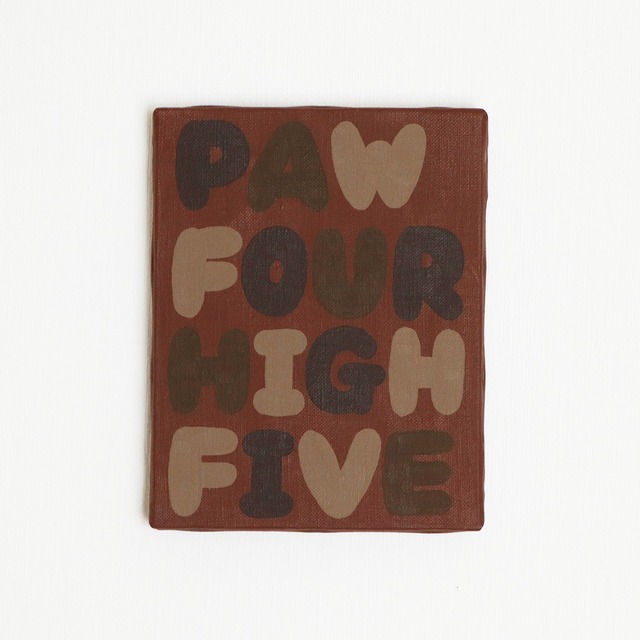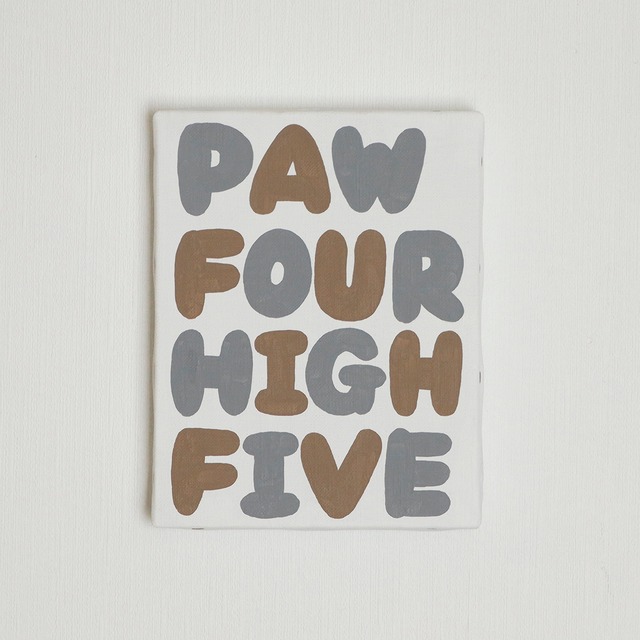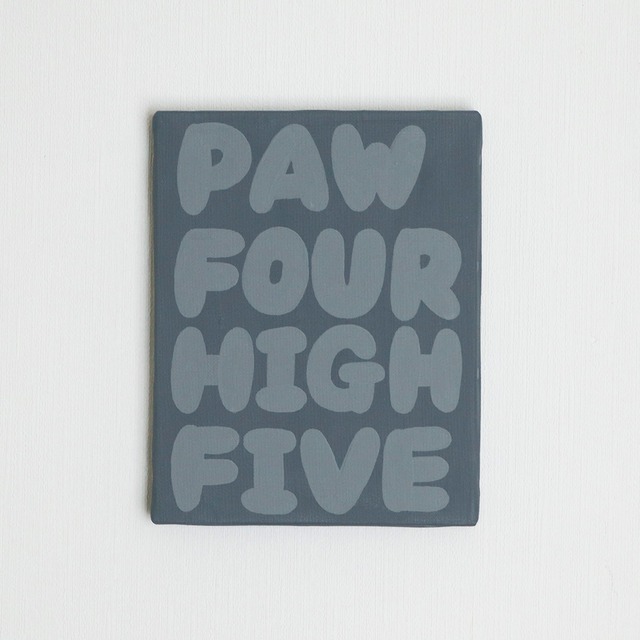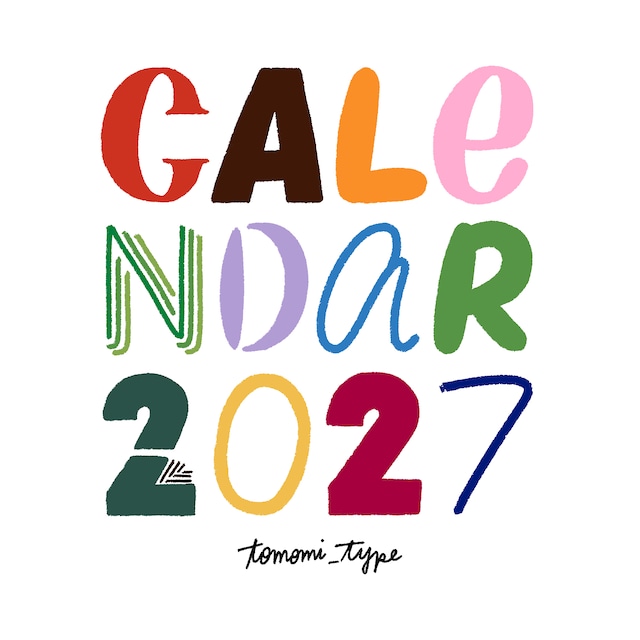
FONT CALENDAR 2027(卓上)
毎年恒例の卓上カレンダーが完成しました! 2027年もワクワクするようなカレンダーに仕上がっています◎ 【1月】Every moment is a fresh beginning / 一瞬一瞬が新たな始まり 【2月】I would rather take chocolate than compliments just now / 今は褒め言葉よりチョコがほしい 【3月】spring fever / (春先のワクワクした高揚感のこと) 【4月】Good luck with your APRIL start! / 4月の新しいスタートに幸運を! 【5月】Smell that fresh MAY air / 新鮮な5月の空気を感じましょう 【6月】Right as rain / 順調そのもの 【7月】catch some waves / チャンスを掴む 【8月】Life is full of ups and downs / 人生は山あり谷あり 【9月】Open book / (多様な考えに寛大であること) 【10月】The fruit of your own hard work is the sweetest / 努力は身を結ぶ 【11月】Good talking to you & Have a good day! / 話ができて良かったです & 良い1日を! 【12月】Everything will turn out for the best / すべては最高の結果になる ----------------------- 【サイズ】 納品時:10.5cm×20.5cm 組立後:10.5cm×16.5cm(h)×9cm
words flower CALENDAR 2027(壁掛け/A4サイズ)
words flowerシリーズは、文字だけで描いたお花です。 今回なんとカレンダーにしました! その月の誕生花を描いています。 A4サイズの壁掛けタイプです。 画鋲やフックなどを使って飾れます(針は少し長めものだと安定すると思います) ポスターのように楽しんでいただけたら嬉しいです◎ 【1月】スイートピー 【2月】アネモネ 【3月】チューリップ 【4月】アルストロメリア 【5月】カーネーション 【6月】アジサイ 【7月】トルコキキョウ 【8月】ヒマワリ 【9月】ダリア 【10月】ガーベラ 【11月】ユリ 【12月】バラ ※誕生花には諸説あります。 ------------------ 【サイズ】 A4サイズ
HANDWRITTEN FONT DICTIONARY LESSON BOOK/ 文字ばかり描いてるイラストレーターのオリジナルフォント描き方練習帖
\オリジナルフォント描き方練習帖ができました!/ オリジナルフォント字典のLESSON BOOKが完成! 「HANDWRITTEN FONT DICTIONARY」を発売してから、 「マネしたいけど上手く描けません…」というお声をいただくことが増えました。 であれば、トモミタイプのオリジナルフォント専用LESSON BOOKを作ろう! となりまして、ついに2冊目となる本が完成しました〜!!! 上手く描けるようになるコツ、フォントのアレンジ法、少しですが新しいフォントも載っています。 この本だけでも楽しめますが、HANDWRITTEN FONT DICTIONARYがお手元にあると より文字を描くのが楽しくなると思います◯ ぜひこれを見ながらたくさん手描きしてみてくださいね^^ ※アレンジ、描き方のページのSNS投稿などはご遠慮ください。 【サイズ】14×14×1(cm) 【ISBNコード】ISBN 978-4-907151-55-3 C0071 ¥1800E 【ページ数】66ページ
HANDWRITTEN FONT DICTIONARY 文字ばかり描いてるイラストレーターのオリジナルフォント字典
\トモミタイプオリジナルフォント字典ができました!/ 文字ばかり描いてるイラストレーター、トモミタイプのオリジナルフォント字典。 既存のフォントを参考にせず、自分で思いついたフォントを絵のように描く私、トモミタイプ。 普段使いしやすいフォントから、思わず描いてみたくなるフォントや季節限定のフォントなど、133種類を一冊にまとめました。 アルファベット大文字・小文字・数字が掲載されています。(一部除く) 眺めるもよし、見様見真似で描いてみるもよし。使い方はあなた次第です! 【サイズ】14×14×1(cm) 【ISBNコード】ISBN978-4-907151-44-7 C0071 ¥1800E
Habit is a second nature
Habit is a second nature 習慣は第二の天性なり 自分の話になりますが、毎朝日付と曜日を描いてSNSにアップする、という習慣があります。 気づけばもう11年半以上(?!)続けている朝の習慣です(2026年9月現在) 正直辞めどきが分からない感がありますが… それでも「続けている」ということが武器になっているのは事実。 そんな自分の気持ちをちょっとだけ込めた作品になっています。 ○サイズ:約227×158×20mm ◯重さ:約150g ○水性塗料使用 ○壁掛け用紐付(仮結びのため使用する場合はしっかりと結び直してください) ◯送料込み 【金額・送料について】 ¥10,000以上の商品のため送料が無料扱いとなっておりますが、大切な作品なので梱包をしっかりした状態でお届けしたいと考えております。 BASEでは、展示会やPOP UPなどで記載している金額に送料を追加した金額となっております。 対面で販売している時と金額が異なりますので、あらかじめご了承くださいませ。
He that falls today may rise tomorrow
He that falls today may rise tomorrow 直訳だと「今日倒れた人は明日は立ち上がるかもしれない」 日本語のことわざに当てはめるなら「七転び八起き」 フレーズ自体には「8」は入っていませんが、 七転び八起きから取って数字の「8」をモチーフにしています。 今日よりも明日、転んだら起き上がりたい。 へこたれそうな時にオススメの作品です。 ○サイズ:約270×220×20mm ◯重さ:約180g ○水性塗料使用 ○壁掛け用紐付(仮結びのため使用する場合はしっかりと結び直してください) ◯送料込み 【金額・送料について】 ¥10,000以上の商品のため送料が無料扱いとなっておりますが、大切な作品なので梱包をしっかりした状態でお届けしたいと考えております。 BASEでは、展示会やPOP UPなどで記載している金額に送料を追加した金額となっております。 対面で販売している時と金額が異なりますので、あらかじめご了承くださいませ。
NO BOOK NO LIFE
NO BOOK NO LIFE 本なしでは生きられない! よく見ると全部「本」のフォントになっています。 こういう方、たくさんいらっしゃるのでは?と思いながら描きました。 本好きの方へのプレゼントにも良いですね◎ ○サイズ:約270×190×20mm ◯重さ:約180g ○水性塗料使用 ○壁掛け用紐付(仮結びのため使用する場合はしっかりと結び直してください) ◯送料込み 【金額・送料について】 ¥10,000以上の商品のため送料が無料扱いとなっておりますが、大切な作品なので梱包をしっかりした状態でお届けしたいと考えております。 BASEでは、展示会やPOP UPなどで記載している金額に送料を追加した金額となっております。 対面で販売している時と金額が異なりますので、あらかじめご了承くださいませ。
Rain before seven, fine before eleven
Rain before seven, fine before eleven 7 時前の雨は11 時前に上がる イギリスの天気にまつわることわざから。 最初は上手くいかなくてもだんだんと好転する、というフレーズです。 雨と雲と雨が止んだ後の空、水たまりをイメージしたカラーにしました。 ○サイズ:約270×220×20mm ◯重さ:約180g ○水性塗料使用 ○壁掛け用紐付(仮結びのため使用する場合はしっかりと結び直してください) ◯送料込み 【金額・送料について】 ¥10,000以上の商品のため送料が無料扱いとなっておりますが、大切な作品なので梱包をしっかりした状態でお届けしたいと考えております。 BASEでは、展示会やPOP UPなどで記載している金額に送料を追加した金額となっております。 対面で販売している時と金額が異なりますので、あらかじめご了承くださいませ。
Laughter is the best medicine
Laughter is the best medicine 笑いは最良の薬 グダグダ悩んでいても、友人や家族と笑って話しているとスッキリすることありますよね。 笑うって大切!心のお薬! カプセルのイラストにそんなフレーズを詰め込みました。 ○サイズ:約270×220×20mm ◯重さ:約180g ○水性塗料使用 ○壁掛け用紐付(仮結びのため使用する場合はしっかりと結び直してください) ◯送料込み 【金額・送料について】 ¥10,000以上の商品のため送料が無料扱いとなっておりますが、大切な作品なので梱包をしっかりした状態でお届けしたいと考えております。 BASEでは、展示会やPOP UPなどで記載している金額に送料を追加した金額となっております。 対面で販売している時と金額が異なりますので、あらかじめご了承くださいませ。
HAPPY of the world
HAPPY! いろんな国の言葉で、「うれしい」 知っている「うれしい」はいくつありますか? 円形のキャンバスなので、飾り方いろいろ! ○サイズ:約Φ250mm、厚み20mm ◯重さ:約200g ○水性塗料使用 ○壁掛け用紐付(仮結びのため使用する場合はしっかりと結び直してください) ◯送料込み 【金額・送料について】 ¥10,000以上の商品のため送料が無料扱いとなっておりますが、大切な作品なので梱包をしっかりした状態でお届けしたいと考えております。 BASEでは、展示会やPOP UPなどで記載している金額に送料を追加した金額となっております。 対面で販売している時と金額が異なりますので、あらかじめご了承くださいませ。
The flower that blooms in adversity is the rarest and most beautiful of all
The flower that blooms in adversity is the rarest and most beautiful of all 逆境の中で咲く花は、どの花よりも貴重で美しい 世の中にはいろんな花があるように、 それぞれがたくましく自由に咲いているイメージで描きました。 文字の色は花の色、葉っぱの色を表現しています。 キャンバスをはみ出すくらい、のびのびと咲き誇りましょう◎ ○サイズ:約333×220×20mm ◯重さ:約200g ○水性塗料使用 ○壁掛け用紐付(仮結びのため使用する場合はしっかりと結び直してください) ◯送料込み 【金額・送料について】 ¥10,000以上の商品のため送料が無料扱いとなっておりますが、大切な作品なので梱包をしっかりした状態でお届けしたいと考えております。 BASEでは、展示会やPOP UPなどで記載している金額に送料を追加した金額となっております。 対面で販売している時と金額が異なりますので、あらかじめご了承くださいませ。
POP UPのメインビジュアルで描いた「in bloom」でステッカーを作りました! いつもそばに花束を◎ サイズ:55×70mm
FAVORITE PHRASE2 文字ステッカー
2026年個展「FAVORITE PHRASE2」メインビジュアルのステッカー。 PHRASEは「言葉のフレーズ」以外に「音楽のフレーズ/旋律」の意味でもあります。 全フォント、音楽と楽譜をモチーフにしたものになっています。 音楽やってる方、ぜひ答え合わせしてみてください♪ ◯サイズ 37×66mm
FAVORITE PHRASE2 ポピーステッカー
2026年個展「FAVORITE PHRASE2」メインビジュアルのステッカー。 ポピーの花を「FAVORITE PHRASE」だけで描いています。 大きな花と大きな蕾が気持ちまで明るくしてくれます◎ ◯サイズ 48×80mm
FAVORITE PHRASE2 花束ステッカー
2026年個展「FAVORITE PHRASE2」メインビジュアルのステッカー。 春のお花で描いた花束。 「FAVORITE PHRASE」の文字で花束を結えています。 ◯サイズ 48×74mm